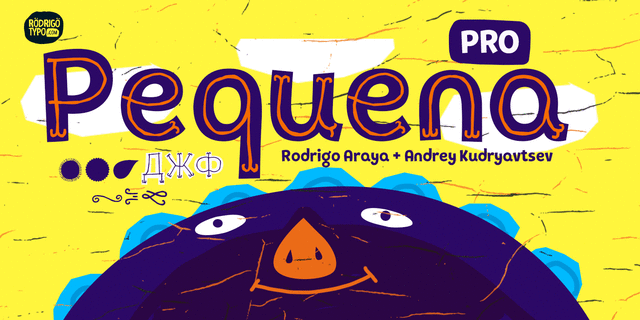
Pequena Pro – это игривое, милое и наивное шрифтоое семейство с двумя алфивитными слоями (жирный гротеск и тонкий рисованный) и двумя неалфавитными (орнаменты и фоны). Идеально подходит для детских книжек и праздничных товаров. Pequena Pro поддерживает множество европейских языков, а также кириллицу. Шрифт разработал в 2016 году Родриго Арая Салас при участии Андрея Кудрявцева.